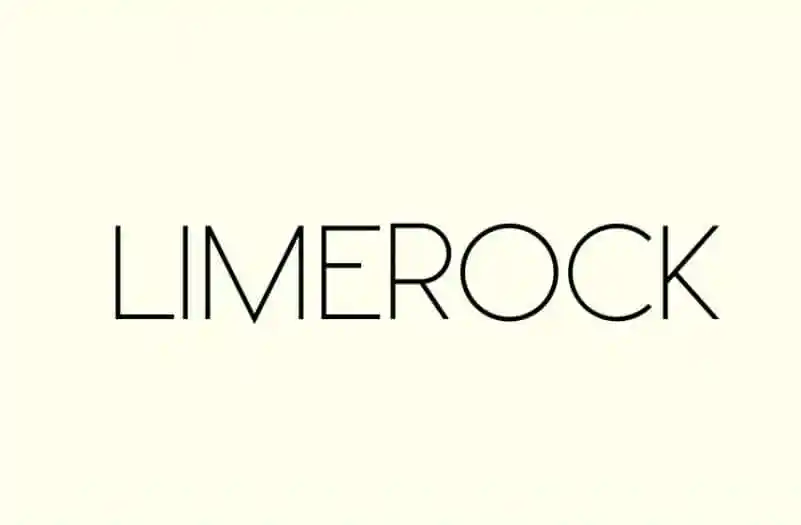
Limerock Sans Serif Font – Download Grátis
Limerock Sans Serif é uma elegante tipografia sans-serif criada pelo designer ECFC, agora disponível para você na sua próxima iniciativa visual. Esta fonte é perfeita tanto para projetos de design tradicionais quanto para as mais inovadoras e atuais. Com seis versões incluídas, além de letras maiúsculas e minúsculas, números, símbolos e conjunto de caracteres multilíngue, Limerock Sans Serif está pronta para trazer um toque sofisticado a qualquer layout ou projeto. Seja você um designer gráfico experiente ou iniciante, este fonte oferece uma variedade suficiente para atender às suas necessidades de design. Descubra o charme e a simplicidade desta nova adição à sua biblioteca de fontes.